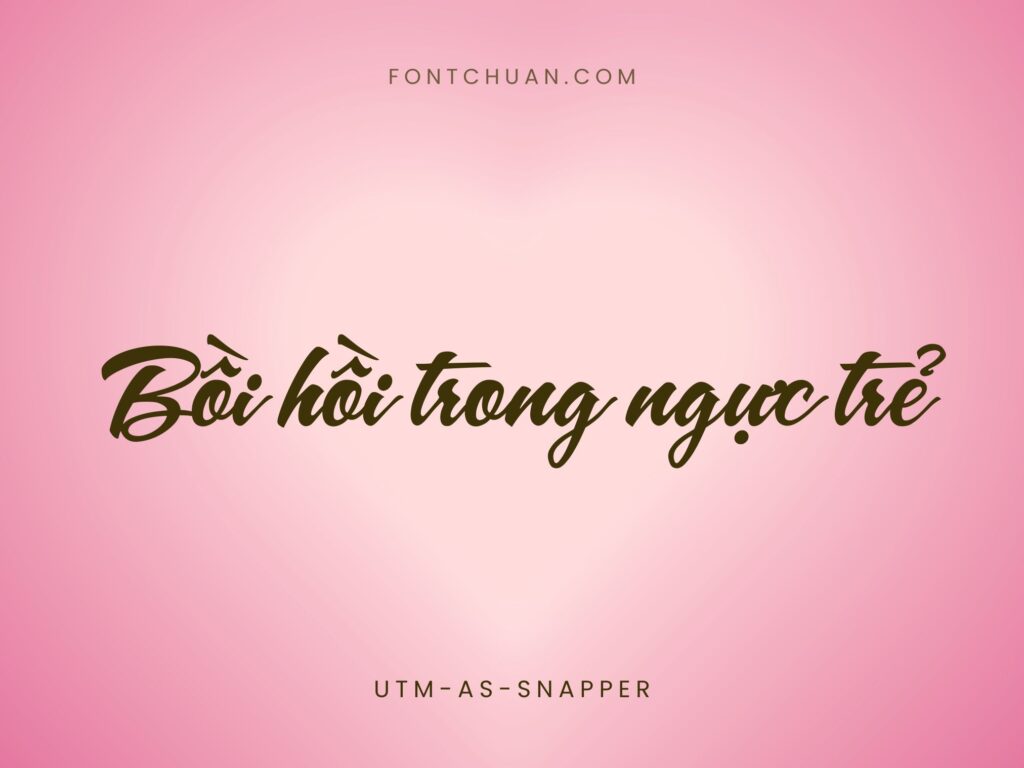
Font UTM A&S Snapper Việt Hóa
UTM A&S Snapper là một Font Script. Nó cũng  là phiên bản Việt hóa của kiểu chữ A&S Snapper Script, một font script mang phong cách viết tay tự nhiên và thanh lịch. Font này được thiết kế bởi Steve Contreras với các đường nét mềm mại, uyển chuyển, tạo cảm giác thân thiện và gần gũi. Phiên bản Việt hóa do Đinh Kiên thực hiện, hỗ trợ đầy đủ tiếng Việt cùng hơn 100 ngôn ngữ khác. Đây là một trong những font được thành viên Font Chuẩn sưu tầm và chọn lọc nhằm phục vụ cộng đồng thiết kế trong các dự án cần sự sáng tạo và cá nhân hóa.
UTM A&S Snapper có cấu trúc chữ nối liền mạch, các nét chữ được thiết kế với độ nghiêng vừa phải và độ dày đồng đều, tạo cảm giác tự nhiên và dễ đọc. Font này phù hợp cho các ứng dụng như thiết kế logo, tiêu đề, bao bì sản phẩm, thiệp mời và các ấn phẩm truyền thông khác. Những ngành nghề như quảng cáo, thiệp cưới, giáo dục và ẩm thực có thể tận dụng UTM A&S Snapper để tạo điểm nhấn độc đáo và thu hút trong thiết kế.